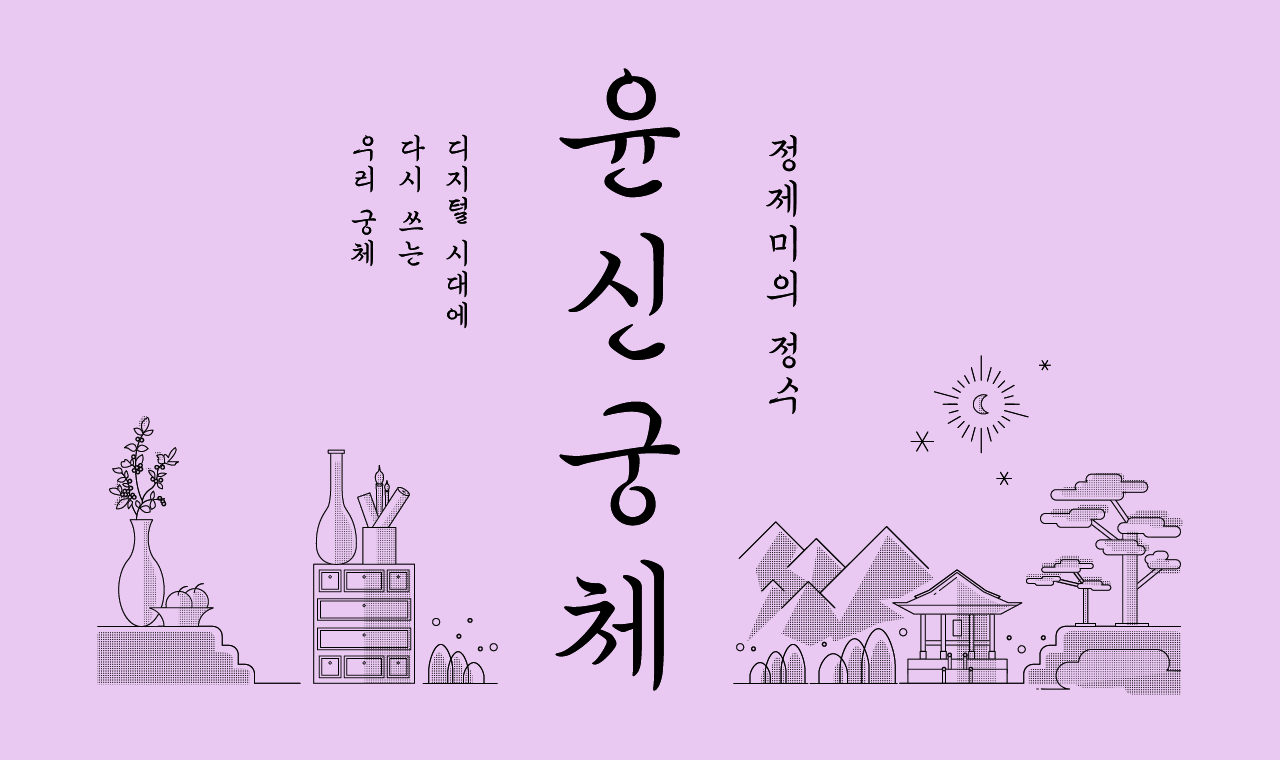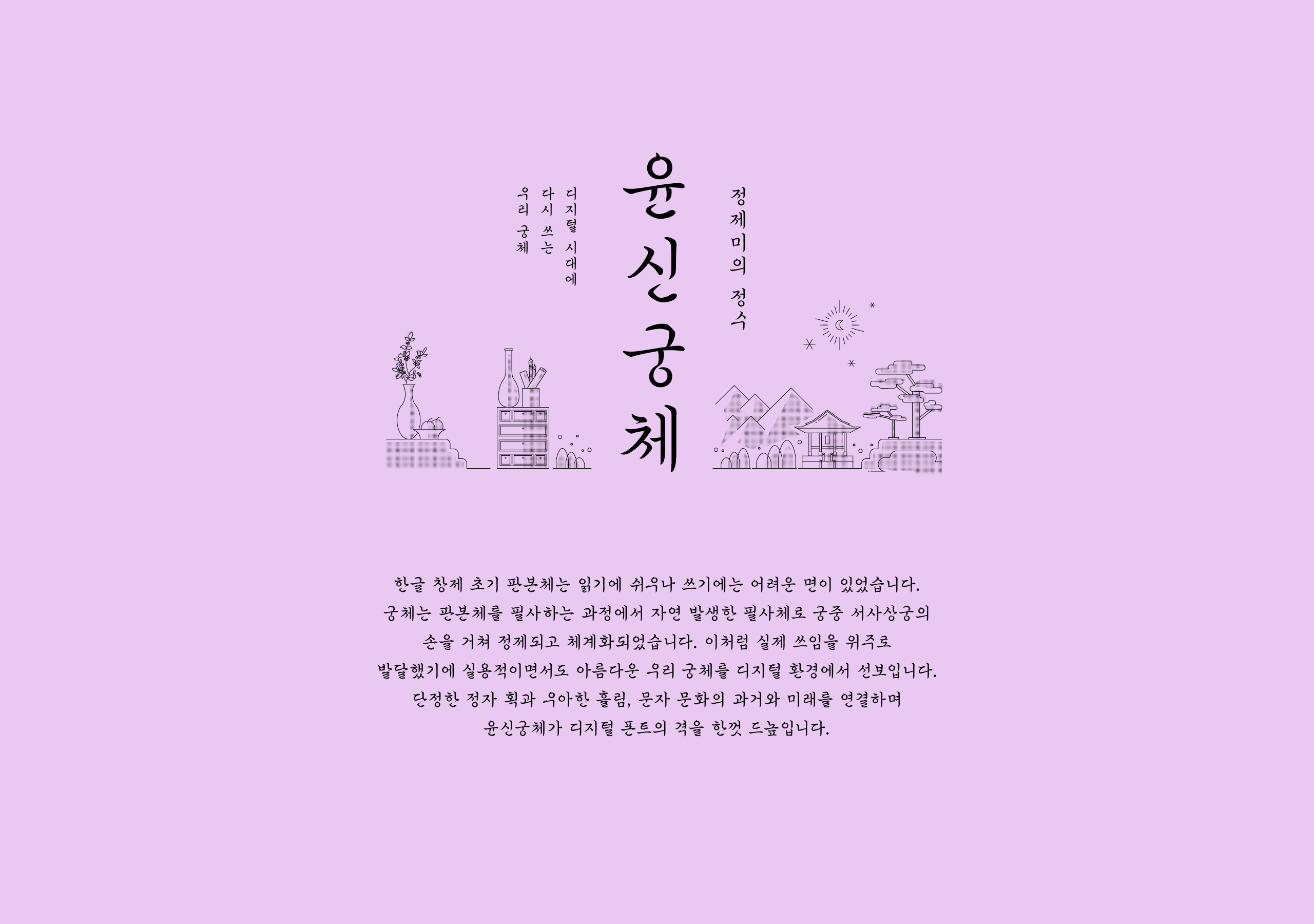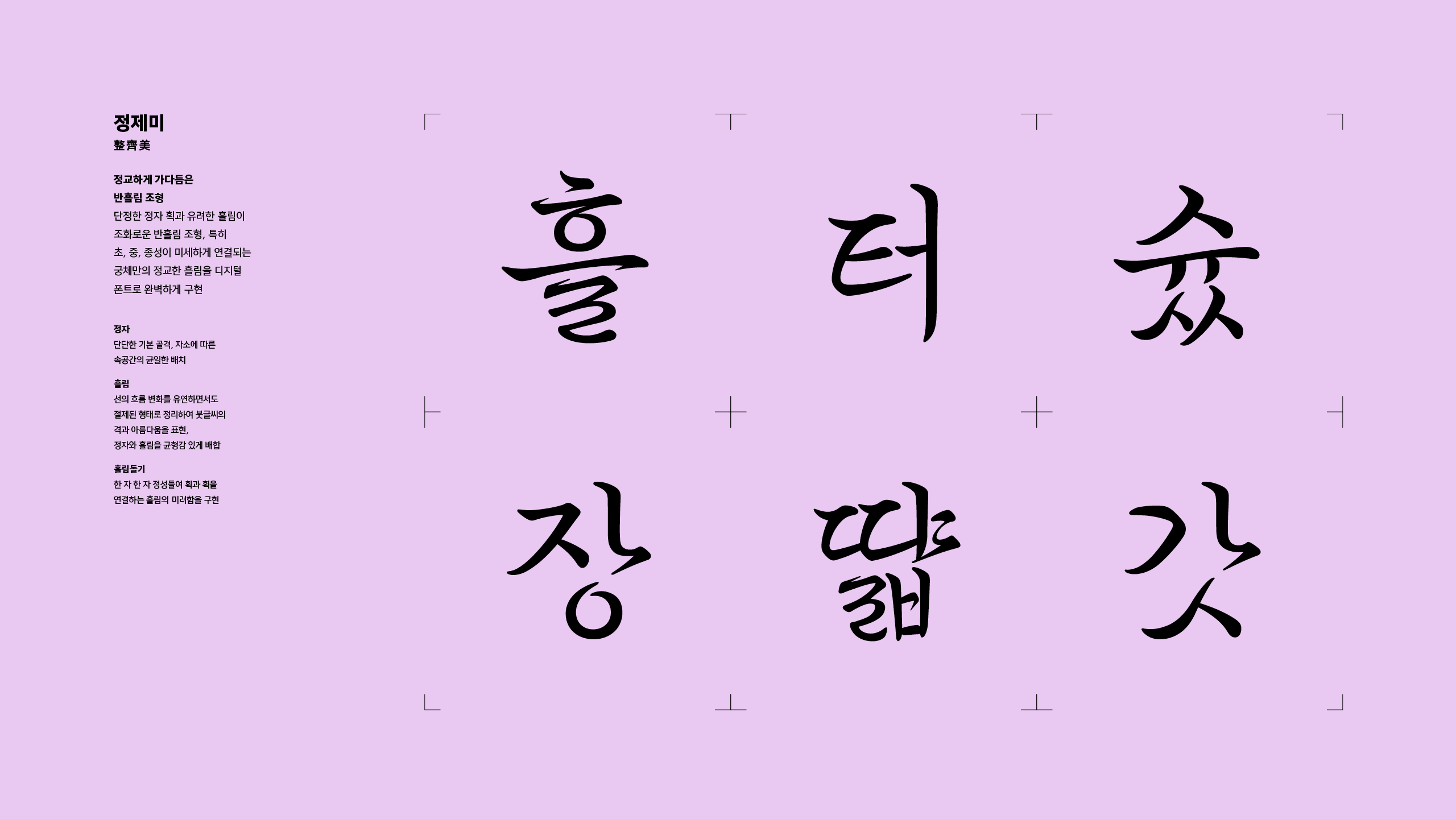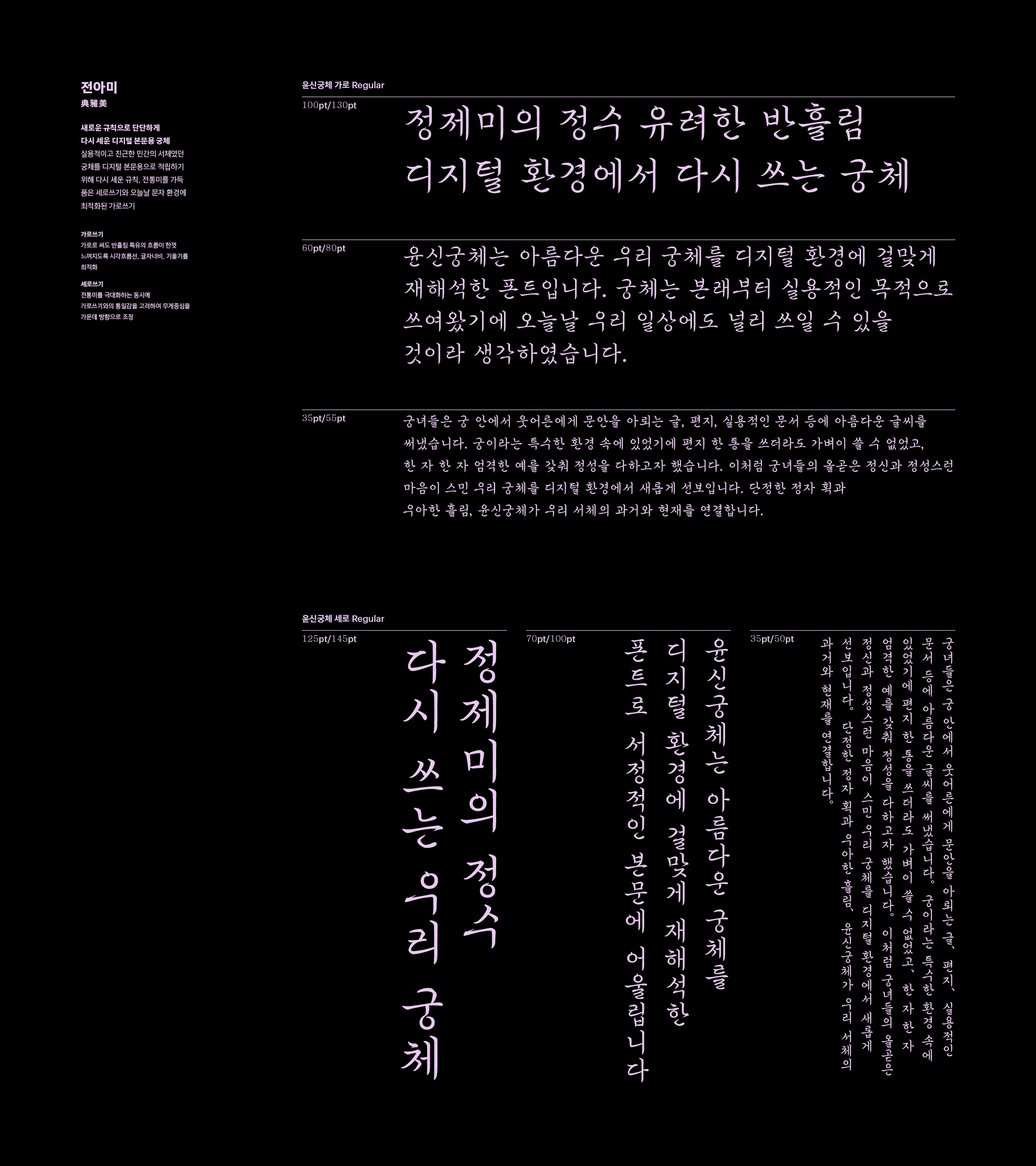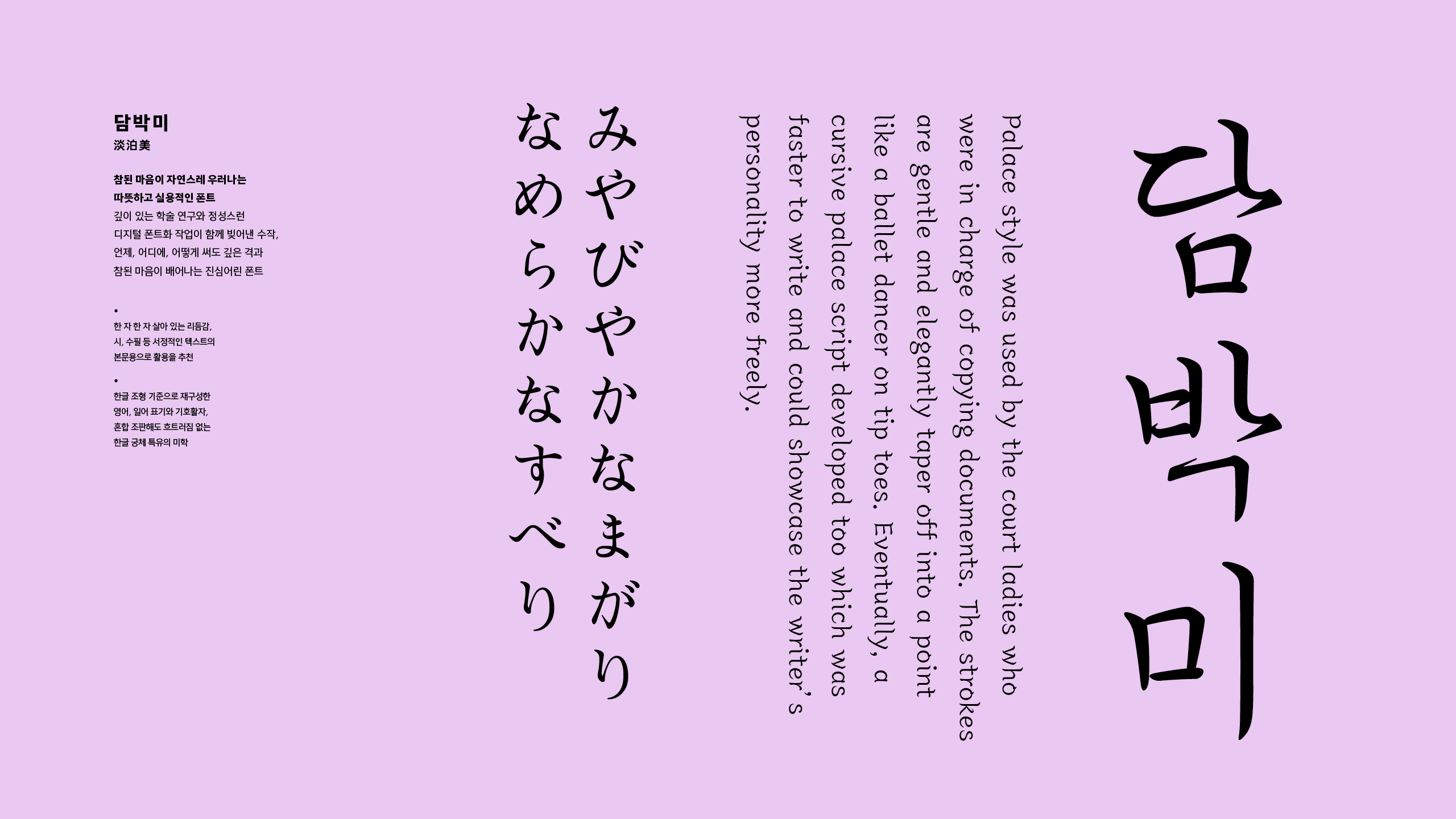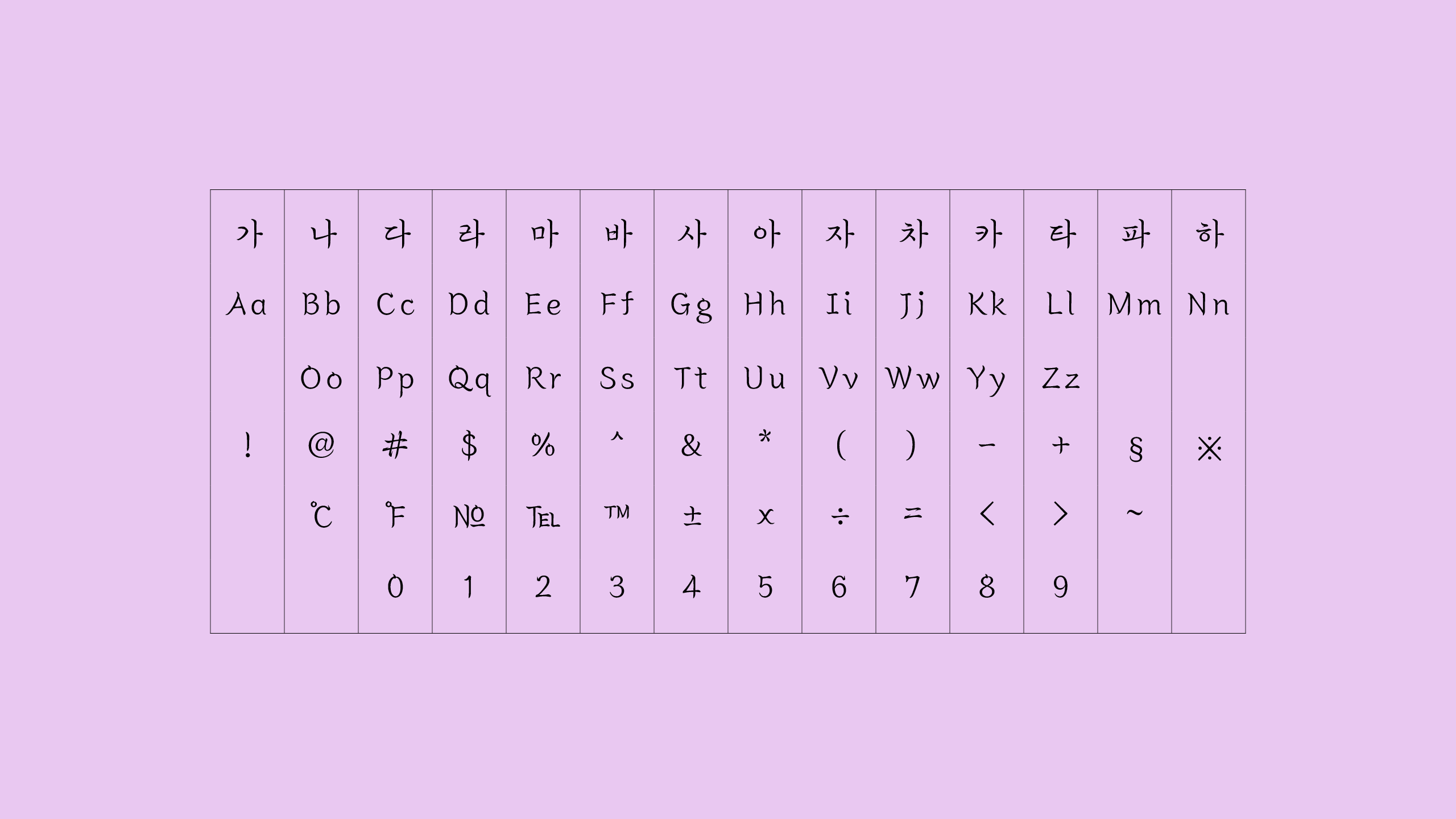
한글 창제 초기 판본체는 읽기에 쉬우나 쓰기에는 어려운 면이 있었습니다. 궁체는 판본체를 필사하는 과정에서 자연 발생한 필사체로 궁중 서사상궁의 손을 거쳐 정제되고 체계화되었습니다. 이처럼 실제 쓰임을 위주로 발달했기에 실용적이면서도 아름다운 우리 궁체를 디지털 환경에서 선보입니다. 단정한 정자 획과 우아한 흘림, 문자 문화의 과거와 미래를 연결하며 윤신궁체가 디지털 폰트의 격을 한껏 드높입니다.
Yoon 윤신궁체 가로·세로